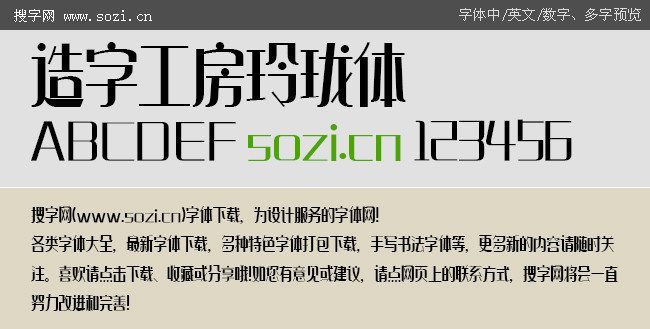
造字工房玲瓏體
搜字網(wǎng)給大家提供一款造字工房玲瓏體中文字體下載,造字工房玲瓏體字體字形瘦長(zhǎng),運(yùn)筆秀巧、粗細(xì)有致、氣韻流暢,在橫折上采取弧化特點(diǎn),靈動(dòng)飄逸。點(diǎn)畫的圓形處理,整體形態(tài)給人以玲瓏雅致之意,其余筆畫的直角的處理又令其彰顯剛毅,有極強(qiáng)的視覺(jué)表現(xiàn)力。 適合女性產(chǎn)品包裝設(shè)計(jì)、網(wǎng)頁(yè)廣告設(shè)計(jì)、圖書封面設(shè)計(jì)等應(yīng)用。(本字體為個(gè)人非商用版,如需要商用請(qǐng)聯(lián)系官方購(gòu)買版權(quán))